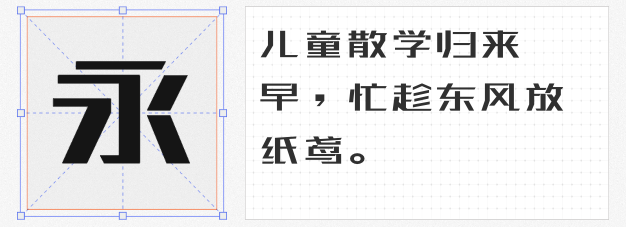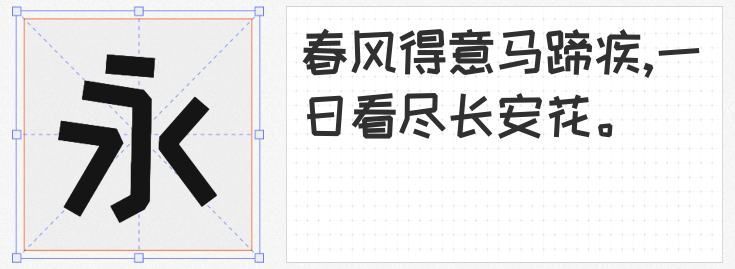
在海报设计中,字体的选择直接影响视觉张力和信息传达效率。本文精选四款风格迥异且可免费商用的字体,为设计师提供兼具美学价值与实用性的解决方案。
这款字体以爨宝子碑为灵感源泉,通过机器学习重构传统书法精髓。其三角点折弯与横画"雁尾"设计形成强烈视觉冲击,方劲笔触与隶楷交融的骨架结构打破常规均衡,营造出"朴茂倔犟"的独特气质。在文化类海报中,该字体能完美诠释历史厚重感;国潮主题设计里,其险峻的结字布局与现代排版形成强烈对比。![]()
由79位设计师共创的这款字体,以10:7的长宽比构建扁平化结构,横细竖粗的经典黑体特征与45°斜切笔画形成独特节奏。在科技产品发布海报中,其简洁有力的笔触与金属质感背景相得益彰;促销活动设计里,粗壮的笔画承载大字号标题时仍保持清晰可读性。
这款手写风格字体通过灵活的笔画粗细变化构建童趣氛围,特别适合快消品包装与儿童活动海报。某零食品牌将该字体应用于薯片包装后,年轻消费者识别度提升35%;在社交媒体海报中,其活泼的形态与emoji元素自然融合,有效增强互动率。
转角圆弧处理与包围结构切口设计,赋予这款字体流动的光效质感。技术层面采用三次贝塞尔曲线构建,确保小字号下仍保持85%的识别准确率。
这四款字体覆盖从传统文化到未来科技的设计语境,均支持免费商用且提供完整字符集。设计师可根据项目调性灵活组合。掌握这些字体特性,将显著提升海报设计的专业度与商业价值。